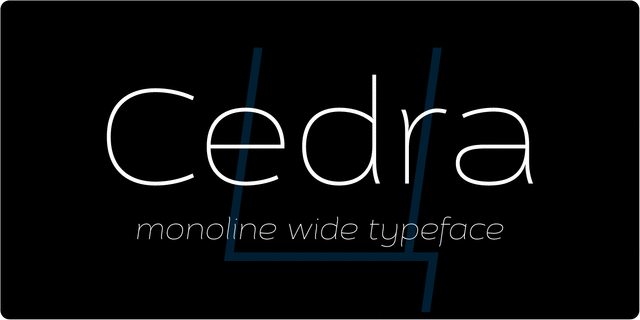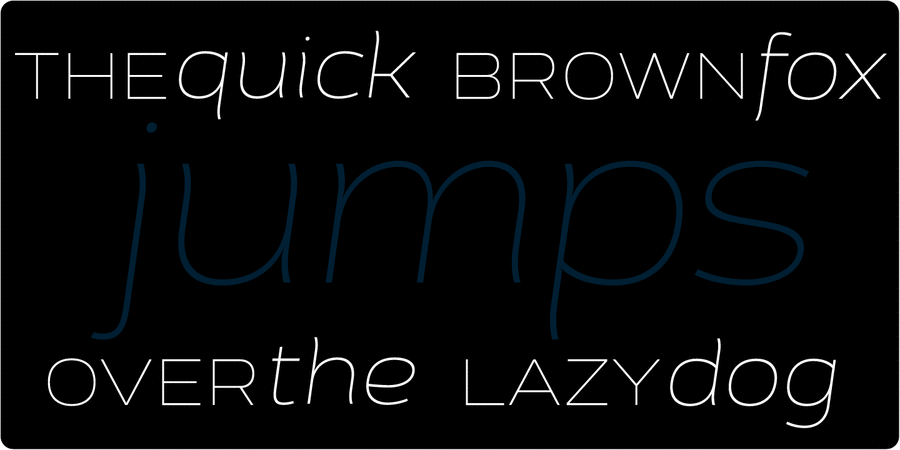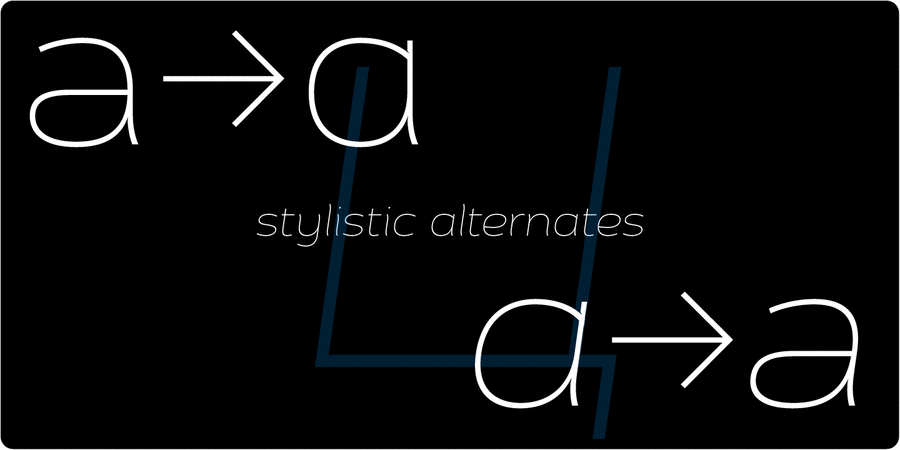
Шрифт Цедра содержит 4 насыщенности и курсивные начертания к ним. Отлично подходит для рекламы, журналов и другой акциденции. Разработан Сергеем Ткаченко в 2010-2013 году.
Associations for font family Cedra 4F WideTypeface personality and character:
delicate, clean, easy, chilly, fresh, fashionable, urban, thin, modern, laconic, freewheeling, weightless, transparent, intimate, fragile, tender, air, wire, green, natural, organic, flexible, peaceful, kind, simple, comfortable, confidence, friendly, polite, eco-friendly, stable
Typeface exhibits stylistic traits:
— Typeface associated with age: